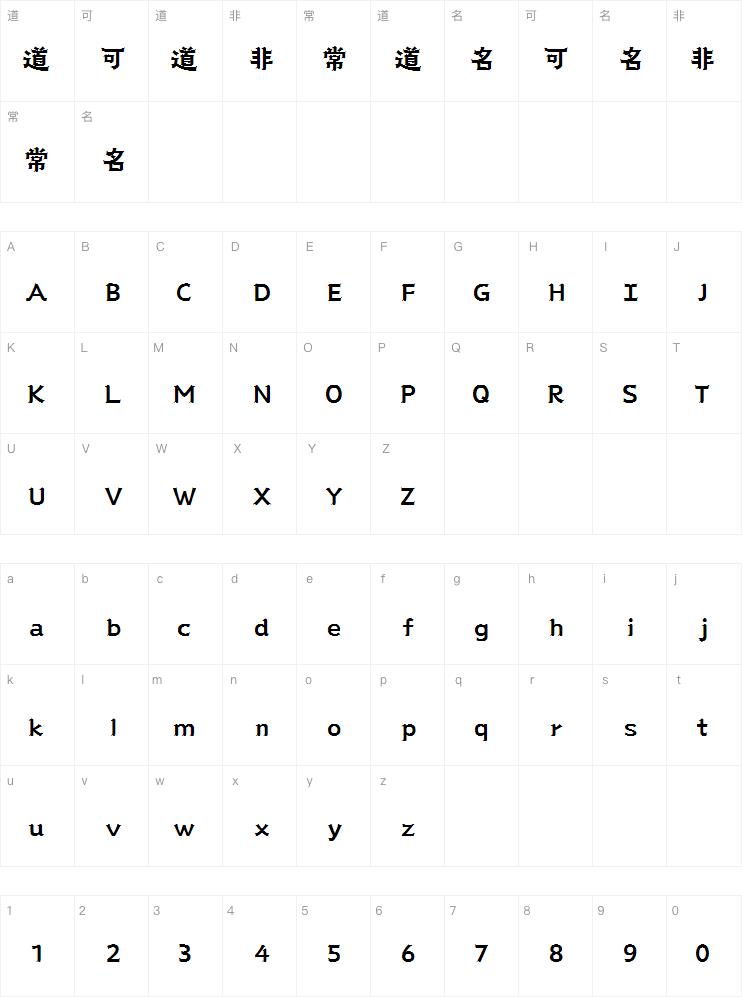
山海星河75W,是一款全新风格的字体,是山海星河字体家族系列中的中等粗细款,编号75W,包含汉字9169个,符号200+个。该字体是一款具有强劲视觉冲击力的字体。字形结构多为方形结构,如正方形、长方形或扁方形,强调字形的稳定性。字形大小悬殊,通过大小不一的字来形成对比和层次感,造型硬朗,直线与曲线结合的笔画构成棱角分明、坚实有力。